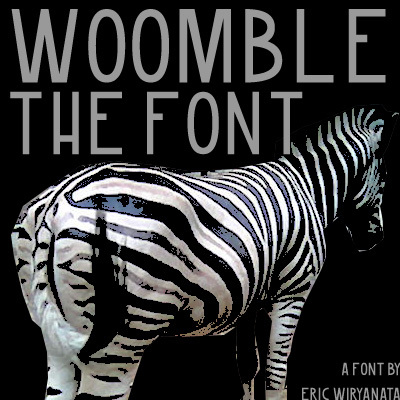
Woomble, di Eric Wiryanata, è un carattere sans serif condensato gratuito, dal look slanciato ed essenziale che trasmette un tono modernista discreto. Le lettere si sviluppano in tratti sottili e uniformi, mentre le forme arrotondate della "O" e i profili dritti conferiscono al font un ritmo pulito, più orientato alla grafica che alla neutralità.
Si adatta perfettamente a poster, copertine di riviste, titoli, wordmark e packaging, dove lo spazio verticale e la silhouette stretta aiutano a mantenere il messaggio compatto. Come font gratuito, Woomble è perfetto per titoli brevi, monogrammi ed etichette che ricercano una presenza nitida e verticale, senza inutili ornamenti.
Il nome Woomble deriva dal frontman di una band.
Il design non è opera sua.
Questa non è la versione completa; molti glifi sono vuoti e non sono inclusi i maiuscoletti.